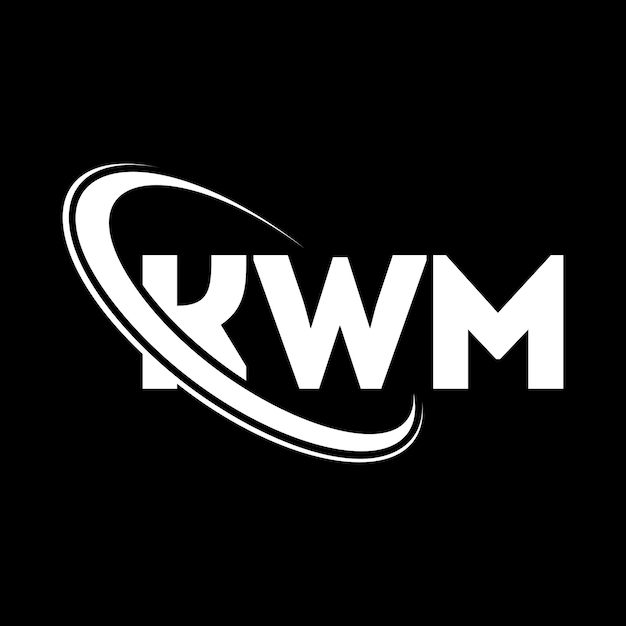
KWM logo KWM litery KWM litera logo projekt inicjały KWM logotyp powiązany z okręgiem i dużymi literami monogram logo kWM typografia dla biznesu technologicznego i marki nieruchomości